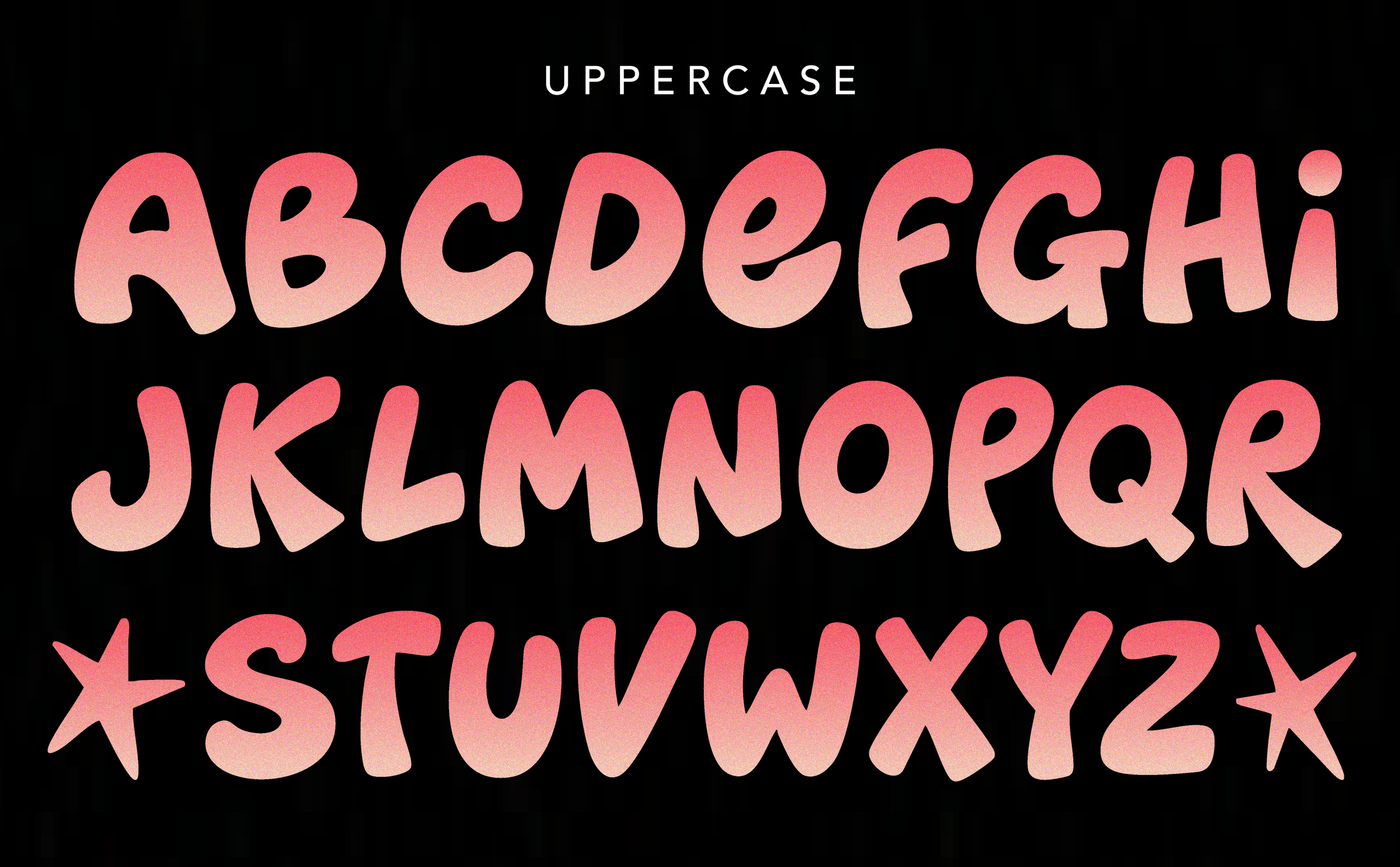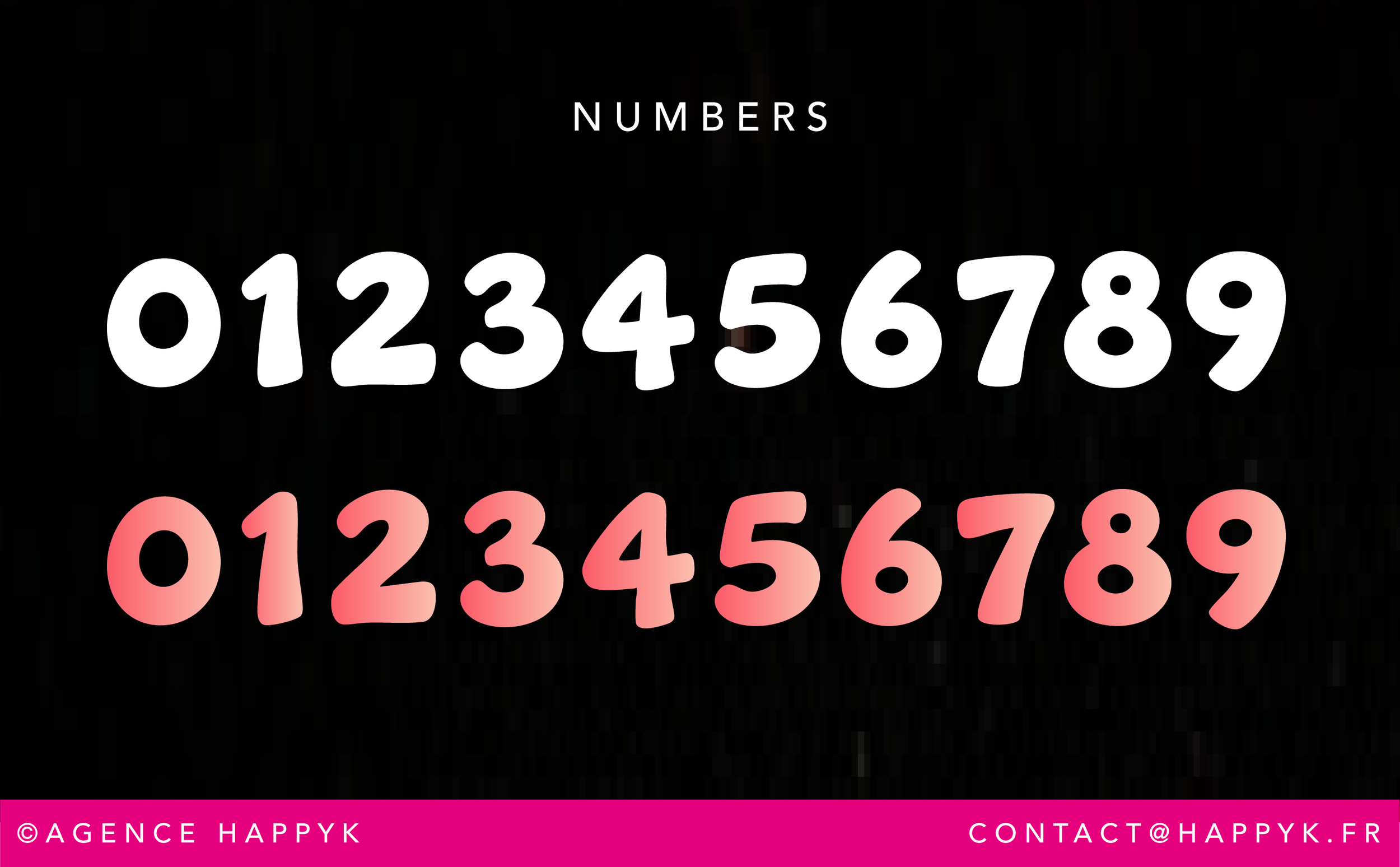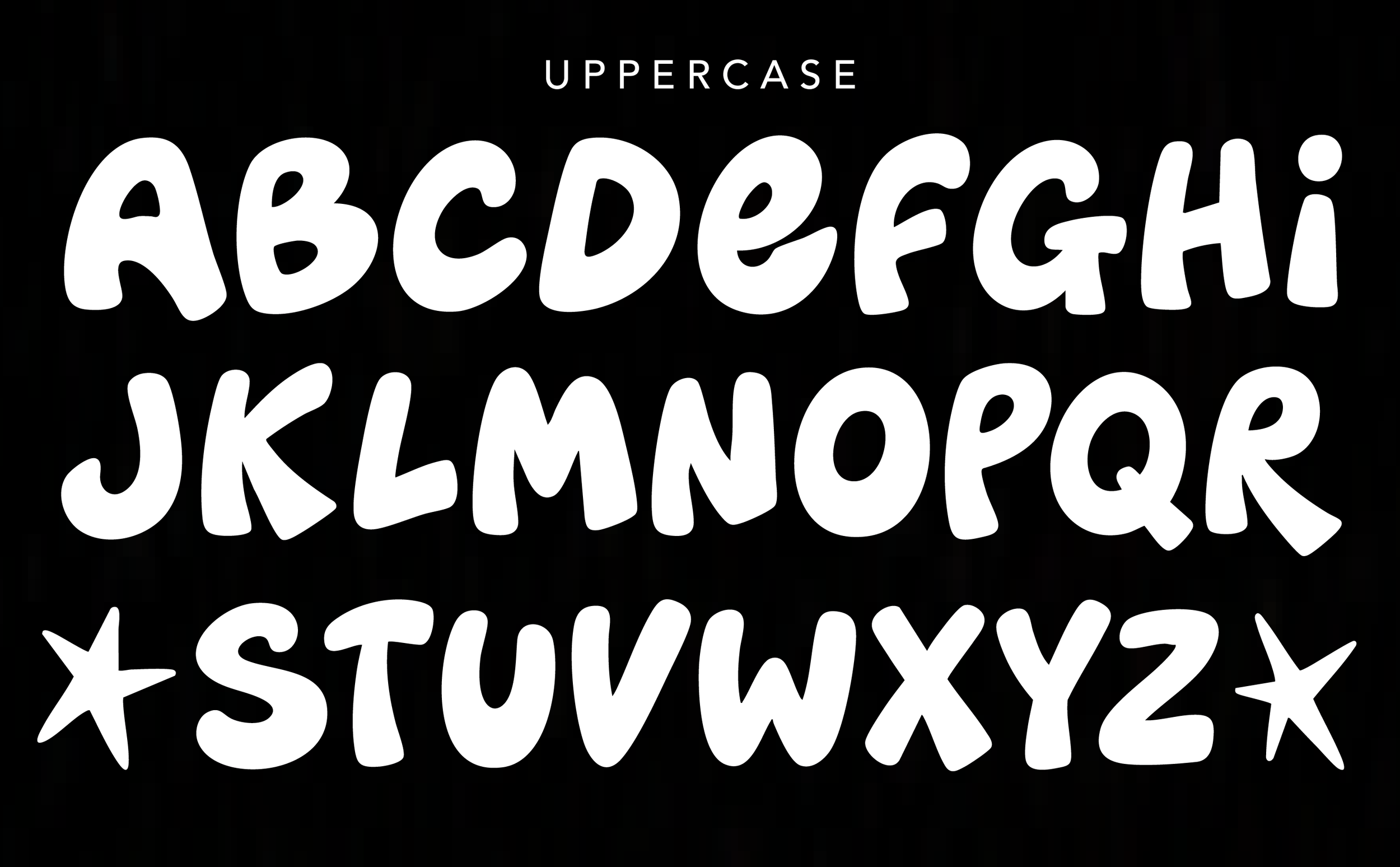
FUNKY_TRESOR
FUNKY TRÉSOR est une typographie inspirée des néons, des pochettes de disques et des nuits qui finissent trop tard.
Ses formes généreuses et son dégradé incandescent lui donnent une énergie rétro-futuriste, entre disco, funk et pop culture.
Pensée pour attirer le regard, elle est idéale pour les affiches, événements, pochettes, logos ou identités qui veulent transmettre du rythme, de la chaleur et une bonne dose de personnalité.
Une typo qui ne passe pas inaperçue. Comme les meilleurs trésors. ✨🪩🔥